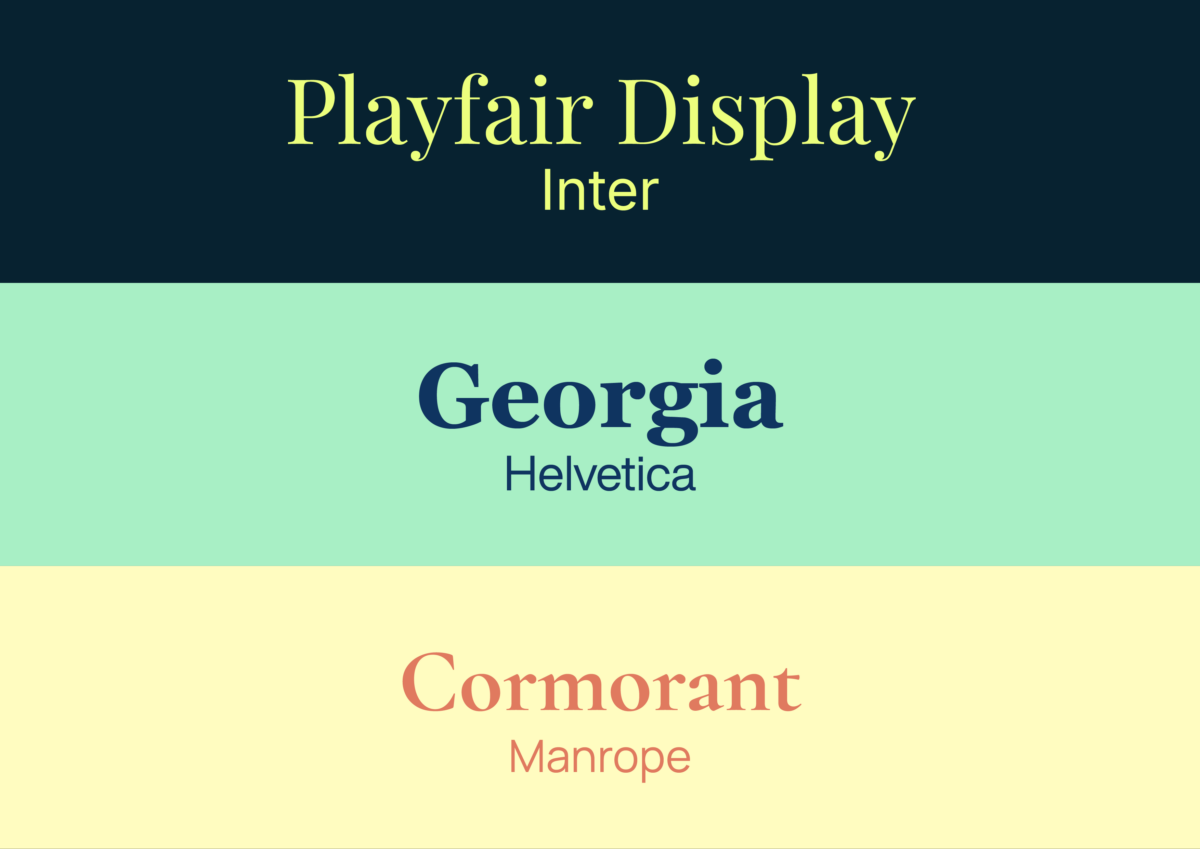
Если ты дизайнер, ты точно проходил через это: выбрал классный заголовочный шрифт, добавил текст под него — и всё, картинка рассыпалась. Шрифты будто ругаются друг с другом. Знакомо? Разбираемся, почему так происходит и как этого избежать.
Когда два шрифта слишком похожи, глаз пытается найти между ними разницу — и не находит. Получается ощущение, будто дизайнер просто не определился. А когда шрифты слишком разные по характеру (например, рукописный рядом с техническим гротеском), композиция разваливается на части, которые не складываются в единое целое.
Хорошая пара — это контраст, но контролируемый. Шрифты должны различаться достаточно, чтобы читался конфликт ролей (один — главный, другой — вспомогательный), но при этом иметь что-то общее: пропорции, настроение, эпоху.
Самое надёжное сочетание — это гротеск (шрифт без засечек) и антиква (шрифт с засечками). Они изначально разные по природе, поэтому не борются за внимание, а дополняют друг друга.
Какую роль отдать какому шрифту — зависит от задачи. Антиква в заголовке считывается как что-то более статусное, редакционное, “взрослое”. Гротеск в заголовке — наоборот, более современно и дерзко. Универсального правила нет, но правило “не больше двух шрифтов на макет” работает в 90% случаев.
1. Playfair Display + Inter — антиква с характером плюс нейтральный гротеск. Хорошо для дизайн-портфолио и редакционных макетов.
2. Georgia + Helvetica (или Arial) — старая добрая пара, которая работает именно потому, что обе гарнитуры спокойные и не тянут на себя внимание.
3. Cormorant + Manrope — более изящный, “дизайнерский” вариант. Cormorant хорош в крупном кегле, Manrope держит мелкий текст без проблем.
Простой тест: поставь оба шрифта рядом на один макет и отойди от экрана (или уменьши масштаб). Если глаз спокойно считывает иерархию — где заголовок, где текст — без напряжения, пара работает. Если в первую секунду непонятно, что главное, а что второстепенное, — пара конфликтует.
И главное правило, которое экономит часы экспериментов: если сомневаешься — бери шрифты из одного шрифтового суперсемейства (например, разные начертания одной гарнитуры). Это не самый смелый путь, зато надёжный.